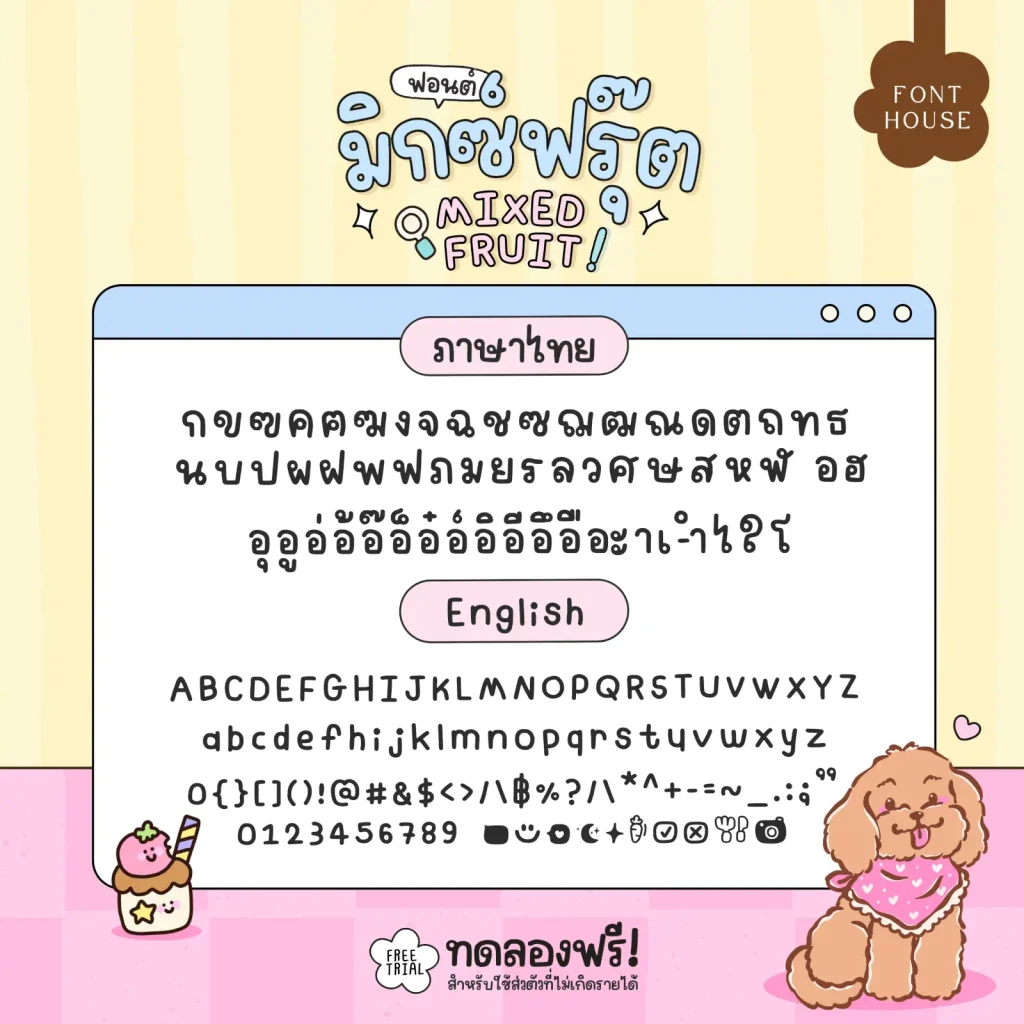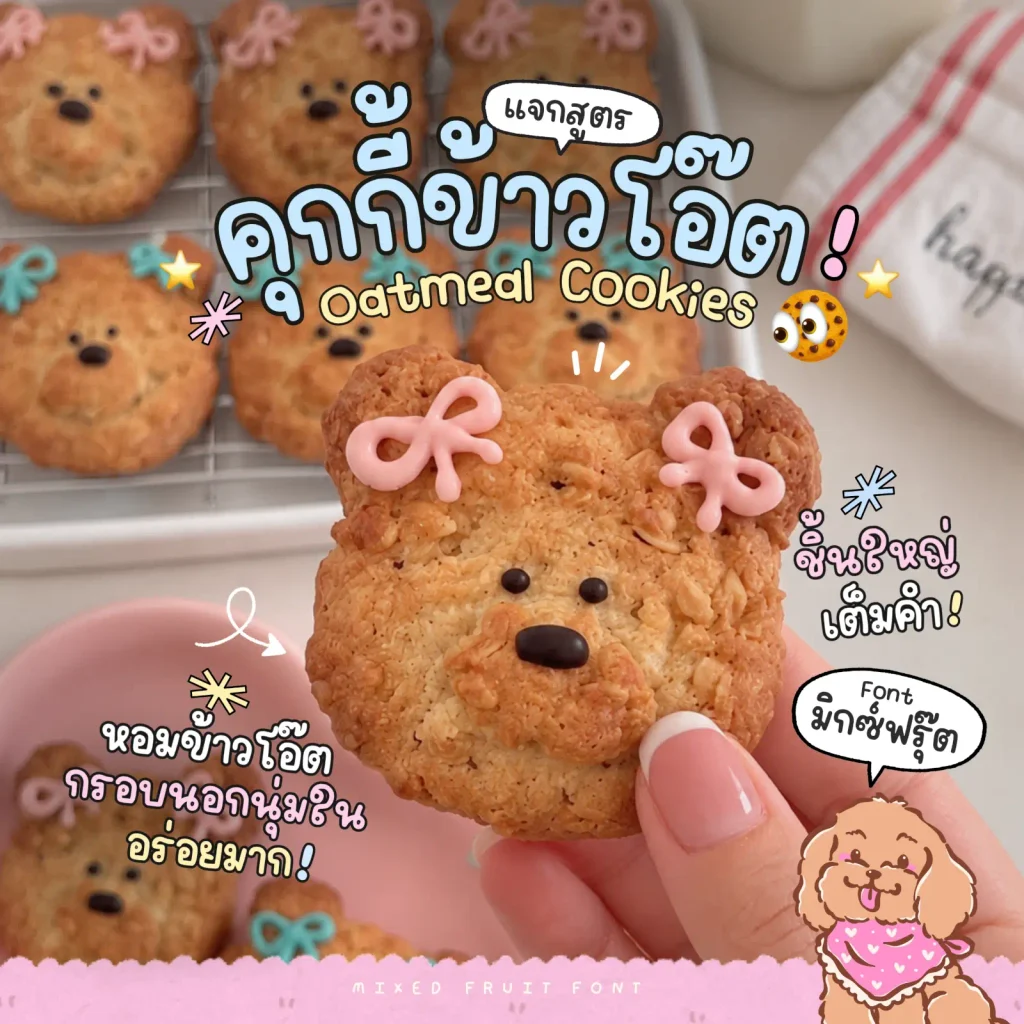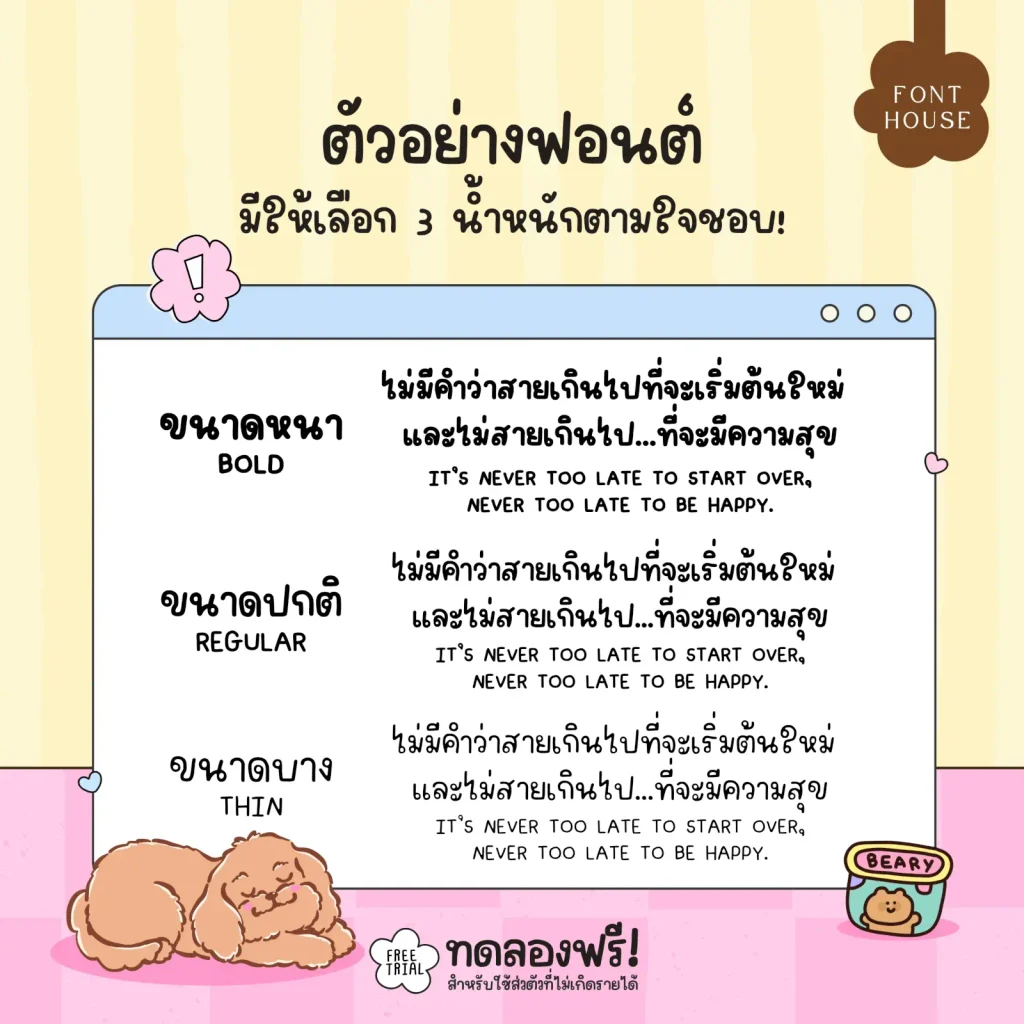
ฟอนต์ มิกซ์ฟรุต (FH Mixed Fruit) – ลายมือสไตล์น่ารัก สดใส ขี้เล่น แต่อ่านง่าย สำหรับงานออกแบบกราฟิก แต่งภาพคอนเทนต์คาเฟ่ หรือโพสต์รีวิวก็ดูน่าสนใจ
- มี 3 น้ำหนัก
มิกซ์ฟรุต (FH Mixed Fruit)